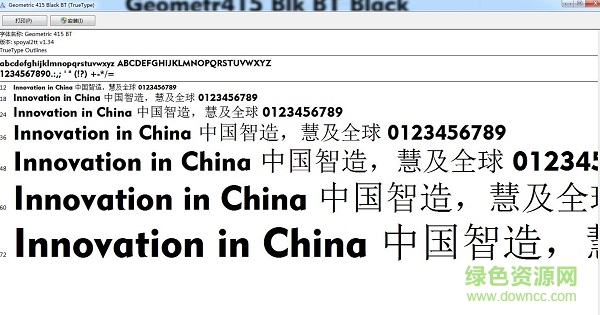
geometric415bt-blacka字體
geometric415bt blacka字體是一款清晰規(guī)范的英文字體,結(jié)構(gòu)清爽,字形明亮,筆鋒犀利,且擁有高分辨率,適合產(chǎn)品宣傳、機械科技等主題,喜歡的朋友快來下載吧!
無襯線字體特點
1.因為無襯線字體通常有藝術(shù)性,因此在顯示器上顯示通常比較賞心悅目;
2.在文字足夠大的情況下,無襯線字體也是同樣可讀的;
geometric415bt-blacka字體
3.無襯線字體種類比襯線字體多得多,因此選擇余地也很大;
4.凡是使用無襯線字體的,必須保證其在正文內(nèi)容中的可讀性。